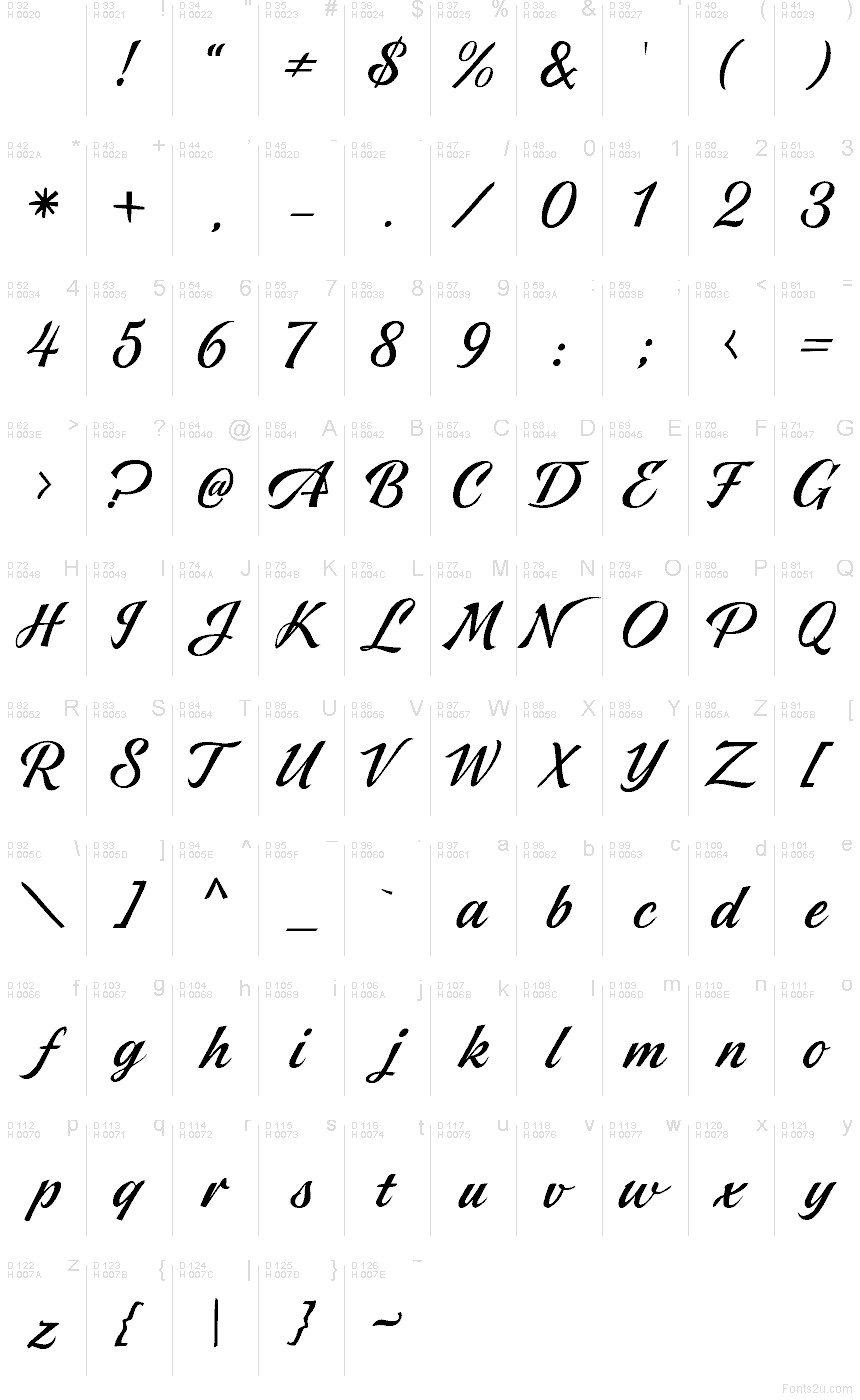
Les Couleurs du Monde
Les Couleurs du Monde от BlackFridayFont — это бесплатный каллиграфический шрифт, выполненный кистью, с размашистым ритмом, напоминающим эскизы в модных журналах. Буквы отличаются длинными, плавными штрихами и изящными изгибами. Сочетание толстых и тонких линий создает ощущение легкости, а не формальности, придавая шрифту расслабленный редакторский вид.
Он отлично подходит для брендинга бутиков, упаковки косметики, меню кафе, заголовков журналов и свадебной полиграфии — везде, где требуется динамика, а не строгость. Будучи бесплатным шрифтом, он также идеально смотрится на титульных карточках, в шапках соцсетей и монограммах, ведь удлиненные начальные и конечные штрихи придают коротким фразам элегантный, «ручной» характер.